글씨 예뻐지는 법! 전문가 추천 꿀팁 7가지 누군가의 글씨를 보면 그 사람의 성격이나 성향까지 짐작하게 되는 경우 있지 않나요? 예쁜 글씨는 단순한 미적 요소를 넘어, 자신을 표현하는 하나의 언어이기도 해요. 특히 손글씨가 점점 희귀해지는 요즘 시대에, 정성스러운 글씨는 더욱 특별하게 느껴지죠.
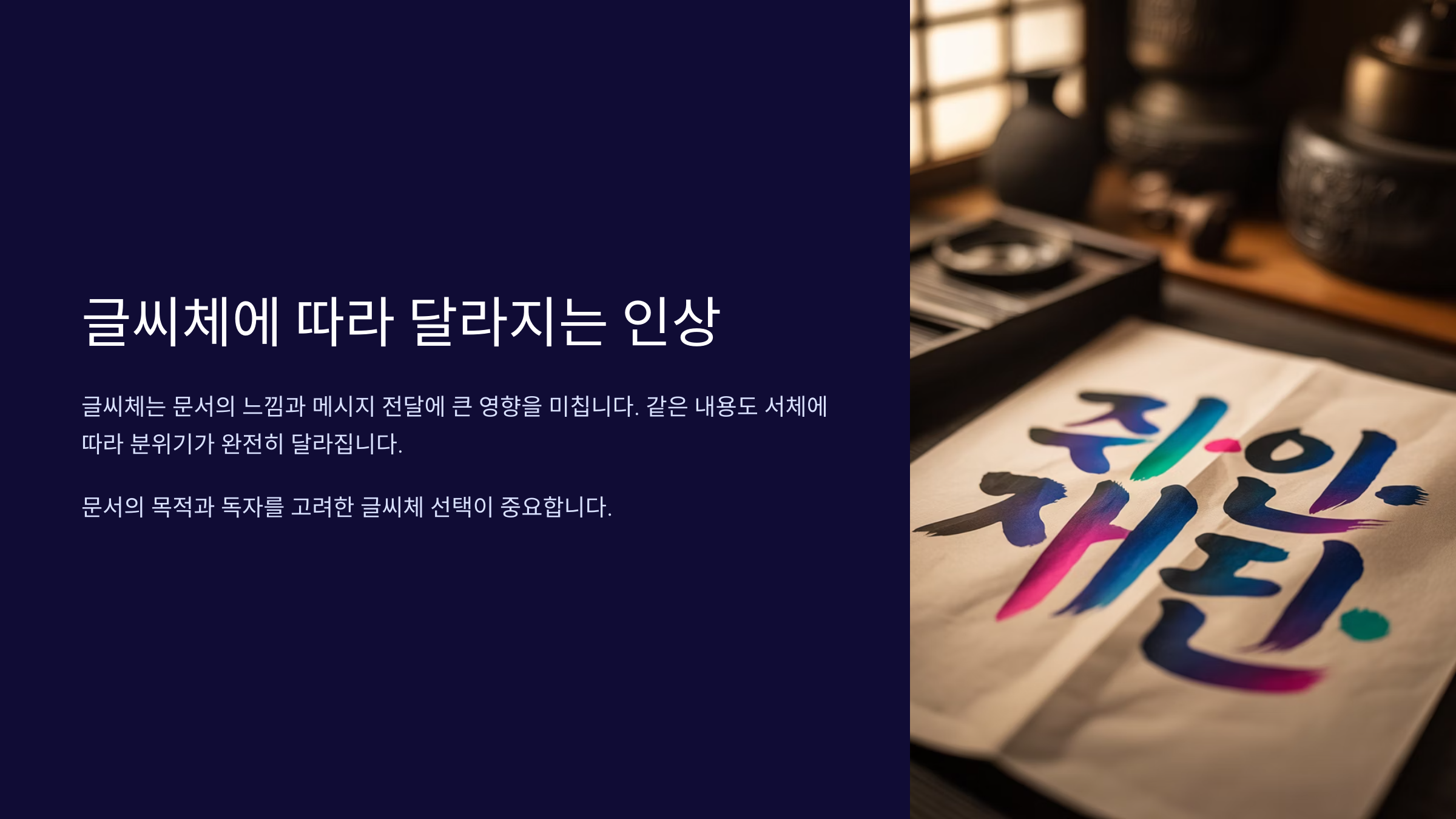
그렇다고 선천적인 재능이 필요하진 않아요! 글씨는 분명히 노력으로 변화시킬 수 있는 분야 중 하나예요. 오늘은 글씨체가 예뻐지고 싶은 분들을 위해, 제가 생각했을 때 가장 효과적이었던 전문가들의 꿀팁 7가지를 알려드릴게요✏
✍ 글씨체에 따라 달라지는 인상
서체의 기본 이해
사람들은 무의식적으로 글씨체를 보고 그 사람을 평가하는 경우가 많아요. 예를 들어, 삐뚤빼뚤한 글씨는 급하고 산만한 느낌을 줄 수 있고, 반대로 반듯하고 일정한 글씨는 정돈된 이미지로 다가오죠. 실제로 면접장에서 작성한 자기소개서나 사내 보고서에서도 글씨체는 무시할 수 없는 인상을 남겨요.전문가들은 "글씨체는 제2의 얼굴이다"라고 말하곤 해요. 특히 교사, 디자이너, 상담사처럼 손글씨를 자주 사용하는 직종에서는 글씨 하나로 신뢰도나 전문성이 결정되기도 한답니다. 이처럼 글씨가 가진 영향력을 이해하는 것이 교정의 첫 걸음이에요.
글씨가 예쁘다는 건 단순히 장식적인 요소뿐 아니라, 읽기 쉬운 구성과 흐름을 가지고 있어야 해요. 글자 간의 간격이나 줄의 정렬도 인상을 좌우하는 중요한 포인트예요. 특히 SNS나 다이어리 글씨에 관심 많은 요즘, 다양한 글씨체 연습을 통해 나만의 스타일을 찾는 것도 중요하답니다.
시중에는 다양한 글씨체 샘플이 나와 있는데요, 유튜브나 인스타그램에서도 셀럽들의 손글씨 영상을 참고해보는 것도 좋은 방법이에요. 그들의 글씨를 보고 '왜 예뻐 보일까?'를 분석해보면 금방 감이 온답니다!
🖋 유명 글씨체 스타일 비교
글씨체 특징 느낌 활용 예시 펜글씨체 균형 있고 깔끔함 단정, 전문적 자기소개서, 다이어리 손글씨체 감성적, 자유로운 형태 부드럽고 따뜻함 편지, SNS 포스트 캘리그래피 예술적이고 개성 강함 개성, 감동적 카드, 인테리어 소품 내가 어떤 분위기의 사람으로 보이고 싶은지를 생각하면서 글씨체를 고르고, 그에 맞게 연습해보는 것이 좋아요. 예쁜 글씨는 그 사람의 성격과도 연결되어 보이기 때문에 글씨체 하나 바꿨을 뿐인데, 삶의 태도까지 바뀐다는 분들도 많답니다😊
📐 기본 구조를 먼저 다잡자!
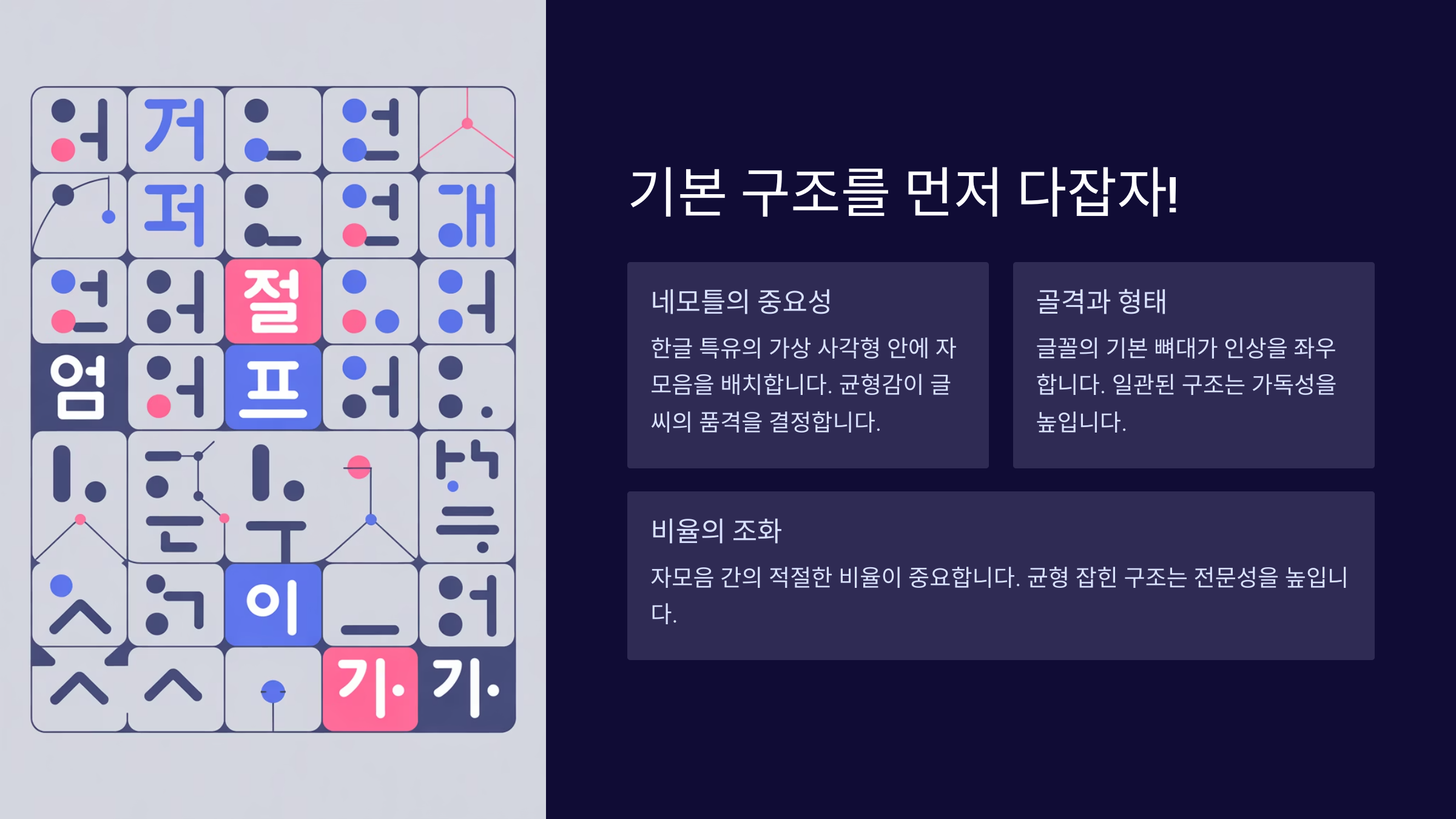
기본 구조를 먼저 다잡자! 글씨체 교정의 핵심은 구조를 잡는 거예요. 구조가 정돈되어 있지 않으면 아무리 따라 써도 일정하지 않고 뒤죽박죽해 보일 수 있어요. 그래서 가장 먼저 해야 할 일은 가이드라인을 활용해 글자의 기준을 정해주는 거예요. 연습노트에 네모 칸이나 줄노트를 사용하면 이 기준을 잡기 좋아요.
한 글자 안에서도 '기본 선'이 무너지는 경우가 많아요. 위, 아래로 치우치거나 좌우 비대칭으로 쓰다 보면 읽는 사람이 피로감을 느끼죠. 그래서 중심선, 기울기선, 높낮이선 등을 생각하며 연습하는 게 좋아요. 특히 초등학교 공책처럼 연습선이 있는 노트는 아주 유용하답니다.
글자의 공간 배치도 중요한데요, 'ㅇ'이나 'ㅎ'처럼 동그라미가 들어간 글자는 너무 크거나 작게 쓰지 않도록 균형을 맞춰야 해요. 연습할 때는 자주 쓰는 단어 위주로 2~3글자 단위 묶음을 연습하는 것도 효과적이에요. 예를 들어 ‘감사’, ‘하루’, ‘기쁨’ 같은 단어를 반복적으로 쓰면 자연스럽게 구조가 정돈돼요.
또 한 가지 꿀팁은 '도형화' 연습이에요. 즉, 글자를 사각형 안에 넣는 연습을 하며 자간과 획의 배치를 눈에 익히는 거죠. 이런 습관을 들이면 나중엔 무의식적으로도 균형 잡힌 글씨가 나와요. 초보자일수록 도형 틀 안에서 쓰는 훈련이 많은 도움이 돼요!
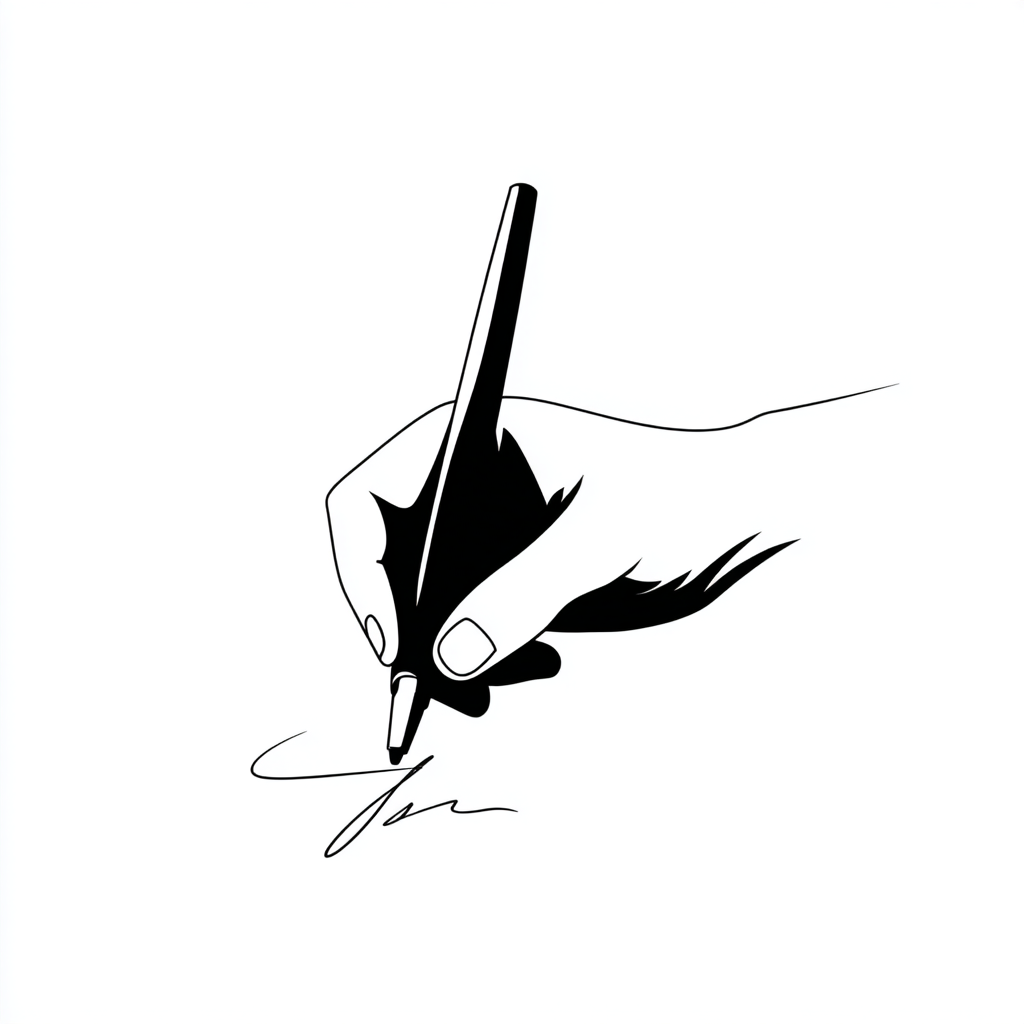
📏 글씨 구조 기준표
항목 설명 체크 방법 기울기 글자가 일정한 각도로 기울어 있는지 확인 줄노트에 대고 쓰며 확인 중심선 글자의 중심이 위 아래로 치우치지 않도록 조절 가로선 기준 중심 맞춤 간격 글자 간 간격을 일정하게 유지 눈으로 맞추기 연습 기본 구조가 무너지면 아무리 예쁜 펜을 써도 의미 없어요. 글자 하나하나를 조각한다는 느낌으로 쓰는 습관이 필요해요. 특히 글씨체를 바꾸고 싶다면, 지금까지의 손글씨 습관을 완전히 리셋하는 자세로 임해야 한답니다. 🎯
📏 줄 간격과 자간의 균형
줄 간격과 자간의 균형
글씨가 예뻐 보이기 위한 가장 중요한 요소 중 하나는 바로 줄 간격과 자간이에요. 아무리 글자 하나하나가 예뻐도 줄이 들쭉날쭉하거나 글자 간격이 좁고 넓으면 전체적으로 정돈되지 않아 보여요. 그래서 초보자분들이 가장 먼저 교정해야 할 포인트가 바로 이 부분이랍니다.줄 간격은 일정해야 해요. 노트에 글씨를 쓸 때 위 줄과 아래 줄의 높낮이가 다르면 전체적인 레이아웃이 무너져요. 처음엔 연습장에 연하게 연필로 줄을 그어가며 간격을 맞추는 게 좋아요. 줄이 일정하게 유지되면 눈으로 보기에도 안정감이 들고, 글씨가 더 깔끔해 보여요.
자간도 무척 중요해요. 글자 사이가 너무 붙으면 답답해 보이고, 반대로 너무 떨어지면 흐트러져 보이죠. 적절한 간격을 유지하면서 글자를 쓰면 가독성이 훨씬 좋아진답니다. 특히 ‘하’, ‘마’, ‘바’처럼 벌어지기 쉬운 글자는 의도적으로 조금 더 좁혀주는 연습이 필요해요.
연습 팁 하나 알려드릴게요! 10개의 같은 글자를 쓰고 그 중에서 자간이 가장 일정한 줄을 골라보세요. 반복하면서 어떤 간격이 가장 보기 좋은지를 눈에 익히는 게 중요해요. 이렇게 감각적으로 배우는 방법은 실제 글씨체 변화에 많은 도움이 된답니다!
📐 간격 조절 연습표
항목 권장 간격 확인 방법 주의사항 줄 간격 문자 높이의 1.5배 눈금자 사용 위아래 기준선 일치 자간 글자 너비의 1/2 사이 간격 눈대중으로 조절 일정하지 않으면 전체 흐름 깨짐 줄 간격과 자간을 신경 쓰면서 글씨를 쓰면, 단어 단위가 아니라 문장 전체가 정리돼 보이기 시작해요. 특히 시험지나 보고서 같은 문서 작성할 때 큰 차이를 느낄 수 있답니다. ✨ 글씨가 안정감을 갖게 되면 보는 사람도 기분 좋아지고, 본인도 자신감이 생겨요!
🖊 필기구의 종류와 각도 조절
필기구의 종류와 각도 조절
예쁜 글씨를 쓰기 위해선 ‘어떤 펜을 쓰느냐’도 정말 중요해요! 글씨가 잘 안 써진다면, 필기구부터 바꿔보는 걸 추천해요. 펜 종류에 따라 손에 느껴지는 촉감도 다르고, 잉크의 흐름도 다르기 때문에 글씨체에 큰 영향을 미치거든요.대표적으로는 볼펜, 젤펜, 만년필, 붓펜 등이 있어요. 볼펜은 일반적으로 많이 쓰지만, 잉크 흐름이 끊기기 쉬워서 초보자에게는 어려울 수 있어요. 반면 젤펜은 부드럽게 써지고 색도 선명해서 교정 연습용으로 인기가 많아요. 특히 0.4mm 정도의 얇은 젤펜이 자간을 조절하기 딱 좋아요!
또 하나 중요한 건 필기 각도예요. 펜을 너무 세우면 손에 힘이 들어가서 글씨가 뻣뻣해져요. 반대로 너무 눕히면 획이 퍼지거나 선이 고르지 않게 나와요. 보통 45도 각도를 유지하면 가장 자연스럽고 부드러운 획이 나와요. 팔과 손목을 편하게 놓고 쓰는 습관을 들이면 훨씬 안정감 있어 보여요.
필기구를 바꾸고 손의 움직임을 개선하기 시작하면, 자연스럽게 글씨체도 부드럽고 예뻐져요. 펜마다 종이에 닿는 감촉이 다르기 때문에, 여러 가지 펜을 시도해보며 본인에게 맞는 도구를 찾는 게 중요해요. 저도 처음엔 비싼 펜보다 손에 착 붙는 젤펜으로 시작했어요😊
🖋 필기구 종류 비교표
필기구 특징 추천 용도 필기감 볼펜 가볍고 흔함 일반 필기 딱딱하고 끊김 있음 젤펜 부드럽고 색 진함 글씨 연습, 다이어리 부드럽고 일정함 만년필 획이 예술적 정갈한 문서 매끄럽고 탄력 있음 붓펜 예술적 표현 가능 캘리그래피 강약 조절 가능 필기구를 잘 선택하고 올바른 각도로 사용하는 건 글씨 예뻐지는 데 큰 역할을 해요. 도구가 다르면 결과도 달라지거든요. 손에 맞는 필기구를 찾는 것부터가 교정의 시작이에요! ✨
📅 꾸준한 연습이 정답이다!
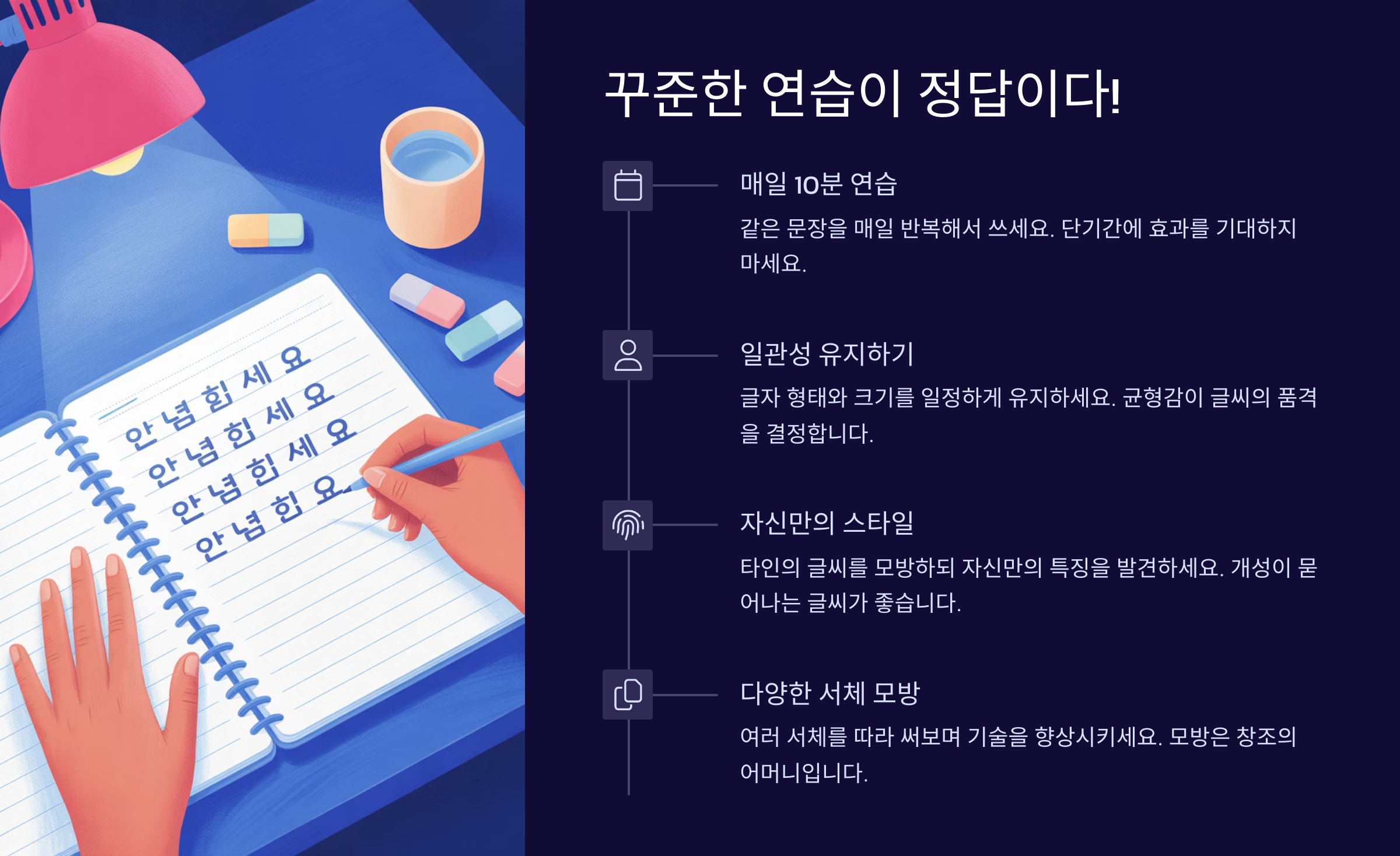
꾸준한 연습이 정답이다!
글씨가 예쁘다고 해서 하루 이틀 만에 이루어지는 것은 아니에요. 예쁜 글씨는 꾸준한 연습에서 나오죠. 제가 생각했을 때, 가장 중요한 것은 바로 '매일 조금씩 연습하는 습관'이에요. 특히 처음에 글씨체가 엉망이더라도 포기하지 않고 계속 써보면, 자연스럽게 개선되는 걸 느낄 수 있어요.하루에 10분, 20분씩이라도 정해놓고 글씨 연습을 하면 눈에 띄게 좋아져요. 예를 들어, 아침에 일어나서 5분 동안 오늘의 계획을 적어보는 것만으로도 글씨체에 도움이 돼요. 처음에는 글씨가 고르지 않지만, 꾸준히 하다 보면 점점 안정감을 찾게 돼요.
저는 글씨 연습을 할 때, 종종 '오늘 하루의 목표'나 '감사한 일'을 적어보곤 했어요. 그런 글귀를 쓰다 보면 무심코 똑같은 글자를 반복하게 되고, 자연스럽게 자주 쓰는 글자는 더 예쁘게 나오는 걸 경험했죠. 이렇게 글을 쓰는 과정에서 개선이 되니, 마치 일기처럼 의미 있는 연습이 되더라고요!
그리고 중요하게 생각해야 할 점은 '나만의 스타일'을 찾는 거예요. 다른 사람의 예쁜 글씨를 따라 하는 것도 좋지만, 결국에는 자신만의 스타일을 만드는 것이 목표가 되어야 해요. 하루하루 조금씩 연습하며 나만의 글씨체를 만들다 보면, 어느 순간 자신만의 독특한 글씨체가 만들어져요!
🖊 매일 연습할 수 있는 글씨 연습표
연습 항목 목표 추천 연습 시간 기본 글자 연습 자주 쓰는 글자에 집중 10분 단어 연습 이해하기 쉬운 단어 연습 15분 전체 문장 연습 실제 사용할 문장 연습 20분 매일 조금씩 연습을 쌓아가다 보면, 글씨는 물론이고 손글씨를 쓰는 자신감도 자연스럽게 키울 수 있어요. 처음엔 힘들겠지만, 꾸준히 하다 보면 어느새 예쁜 글씨체가 내 손에 익어있을 거예요. ✨
📖 예쁜 글씨 따라 쓰기의 힘
Q5. 따라 쓰기 연습은 어떻게 시작해야 하나요?
A5. 처음에는 자주 쓰는 글자나 단어부터 시작해보세요. 그 글씨체를 반복해서 따라 쓰면 자연스럽게 글씨가 예쁘게 바뀌어요. 단계별로 연습하는 것이 효과적이에요.
Q6. 글씨체에 자신이 없는데, 어떻게 자신감을 가질 수 있을까요?
A6. 꾸준히 연습하면서 성과를 눈으로 확인할 수 있어요. 점점 나아지는 글씨를 보고 자신감을 얻고, 연습이 쌓일수록 더 자연스럽고 예쁜 글씨체를 만들 수 있답니다!
Q7. 예쁜 글씨체는 시간이 얼마나 걸리나요?
A7. 글씨체는 개인에 따라 달라요. 보통 1~2주간 꾸준히 연습하면 큰 변화가 느껴지기 시작해요. 중요한 건 포기하지 않고 계속 연습하는 거예요. 시간이 지나면 예쁜 글씨체가 저절로 익숙해져요!
Q8. 글씨체 교정 연습에 필요한 도구는 무엇인가요?
A8. 연습용 노트, 가이드라인이 있는 공책, 좋아하는 필기구, 그리고 시간만 있으면 돼요! 중요한 건 자주 연습하고, 글씨체를 고칠 의지가 있는 거랍니다. 도구는 그다지 중요하지 않아요!